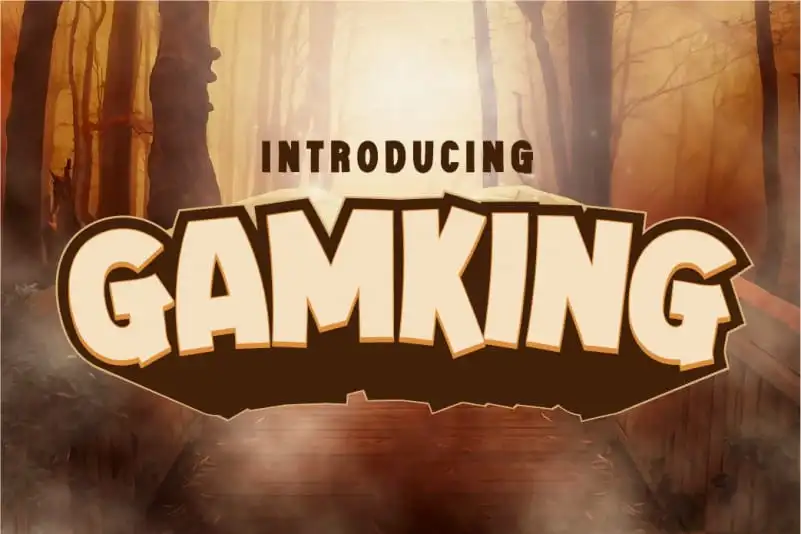
Descubra a Gamking Display Font, uma nova versão com uma aparição moderna e elegante. Ideal para quem busca um estilo sofisticado e flexível, esta fonte apresenta traços firmes, sólidos e claros, características que garantem um visual impactante em seus projetos de design. Ideal para criações visuais agressivas e eficientes, a Gamking Display é perfeita para aplicativos variados como logotipos, anúncios digitais ou qualquer outra forma de propaganda. Seja você uma designer digital experiente ou um iniciante buscando um novo recurso gráfico, essa fonte oferece a chance de inovar e expressar sua personalidade de maneira única. A Gamking Display é mais do que simplesmente um elemento de design; ela é um complemento indispensável para quem busca trazer um toque único aos seus projetos. Se você está procurando por uma fonte com um novo olhar, capaz de se adaptar às suas necessidades específicas, a Gamking Display Font pode ser exatamente aquilo que você precisa.